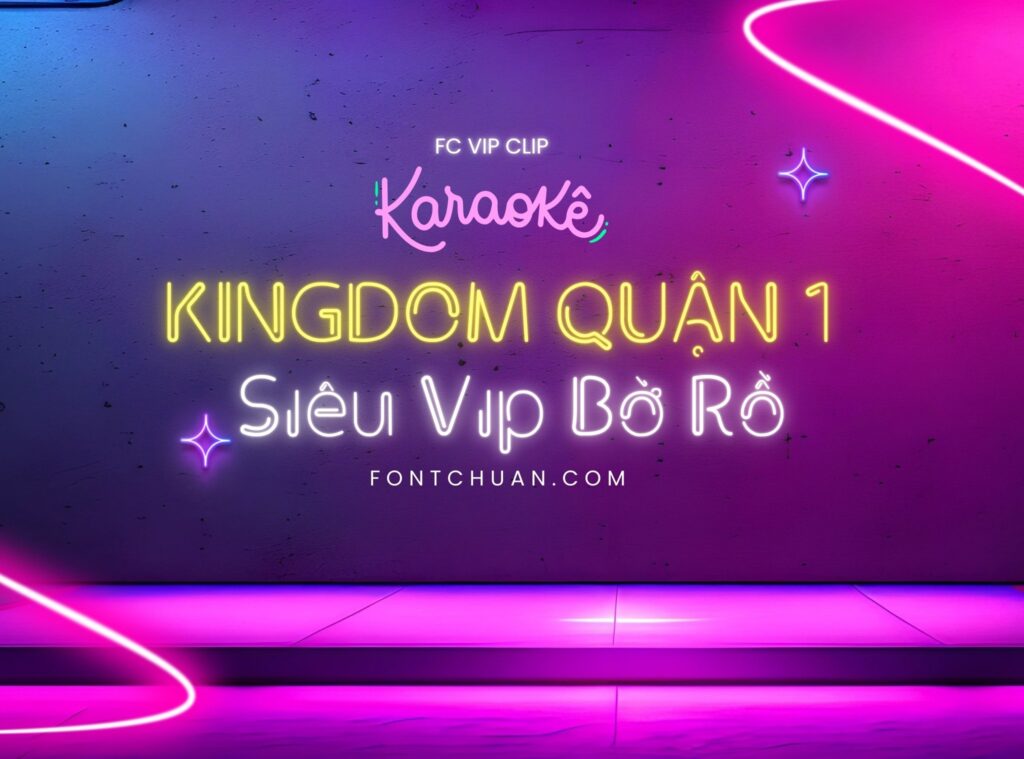
Clip là một Font Sans serif độc đáo được thiết kế bởi Martín Argüello. Font này mang phong cách hiện đại và sáng tạo, đồng thời có thể được sử dụng như một Font Lễ hội để tạo điểm nhấn vui tươi, sôi động cho các ấn phẩm sự kiện hoặc thiết kế quảng cáo đặc biệt. Clip hỗ trợ nhiều ngôn ngữ, giúp nhà thiết kế tiếp cận đối tượng rộng rãi.
Về thiết kế, FC VIP Clip Việt Hóa sở hữu các đường nét sắc sảo và cấu trúc chữ độc đáo, tạo nên sự nổi bật cho bất kỳ dự án nào, Font Chuẩn đã cố gắng giữ lại những đường nét và phong cách nguyên bản của font gốc. Font này lý tưởng cho ngành quảng cáo, thiết kế băng rôn bảng hiệu sử dụng hiệu đèn neon, các tiêu đề, poster và các ấn phẩm quảng cáo khác.